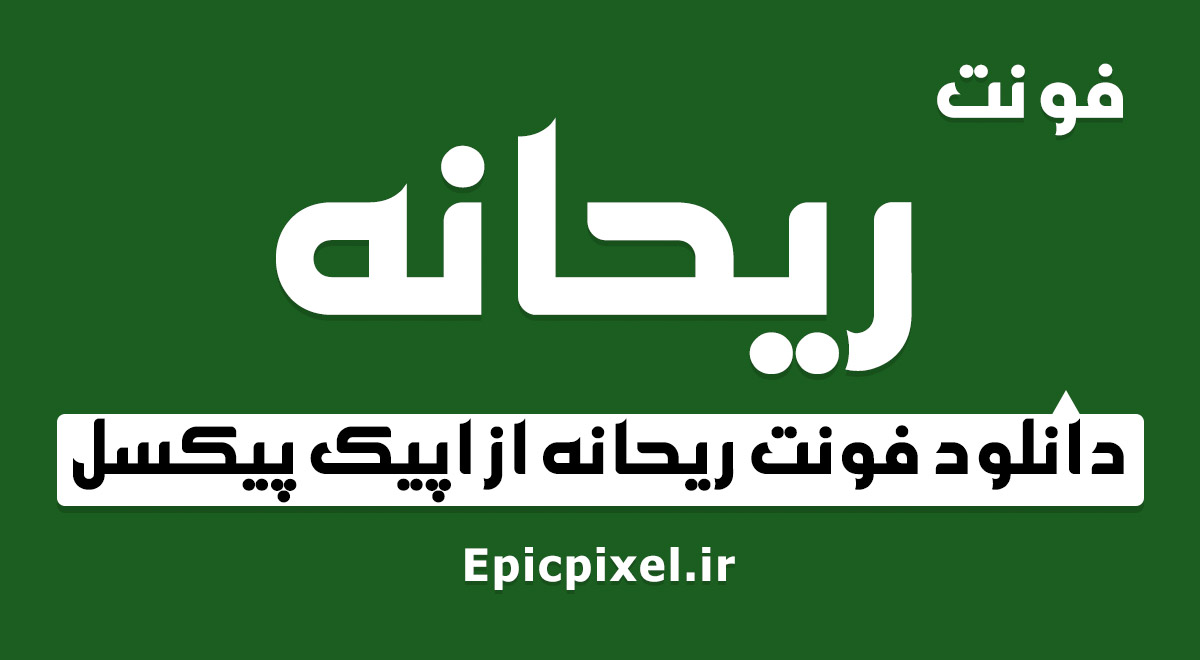
فونت ریحانه فارسی
دانلود رایگان فونت ریحانه، فونتی زیبا و خوانا برای طراحی لوگو، وبسایت، پوستر، بروشور و … . فونت ریحانه با ظاهری اصیل و مدرن، به پروژههای شما جلوهای خاص میبخشد. |
جذابیت اصالت: دانلود رایگان فونت ریحانه برای پروژههای خلاقانه شما
فونت، عنصری کلیدی در دنیای طراحی است. انتخاب فونت مناسب میتواند پیام، احساس و شخصیت خاصی به پروژههای شما القا کند. در میان انبوه فونتهای فارسی موجود، فونت ریحانه با ظاهری زیبا و خوانا، به انتخابی ایدهآل برای طراحان حرفهای و افراد علاقهمند به طراحی تبدیل شده است.
آشنایی با فونت ریحانه: تلفیقی از سادگی و خوانایی
فونت ریحانه، با خطوط صاف و منحنی ملایم، حس مدرن و در عین حال اصیل را القا میکند. این فونت خوانایی بسیار خوبی دارد و برای استفاده در انواع پروژههای گرافیکی، از جمله:
یکی از ویژگیهای قابل توجه فونت ریحانه، پشتیبانی از تمام حروف فارسی، علائم نگارش و اعداد است. این ویژگی باعث میشود تا بتوانید بدون هیچ محدودیتی از این فونت برای نوشتن متن به زبان فارسی استفاده کنید.
دانلود- ظاهری زیبا و منحصربهفرد: فونت ریحانه با طراحی خاص خود، میتواند به پروژههای شما تمایز و جلوهی بصری چشمنوازی ببخشد.
- خوانایی عالی: خوانایی، یکی از مهمترین ویژگیهای یک فونت خوب است. فونت ریحانه خوانایی بسیار بالایی دارد و مخاطب را در خواندن متن دچار مشکل نمیکند.
نکاتی برای استفاده از فونت ریحانه:
- برای حفظ وضوح و خوانایی متن، از فونت ریحانه در سایزهای خیلی کوچک استفاده نکنید.
- فونت ریحانه ضخامت متوسطی دارد. سعی کنید از آن در کنار فونتهای نازک یا ضخیم برای ایجاد کنتراست و تنوع بصری استفاده کنید.
2. آیا فونت ریحانه شامل تمام حروف فارسی میشود؟
بله، فونت ریحانه از تمام حروف فارسی، علائم نگارش و اعداد پشتیبانی میکند.